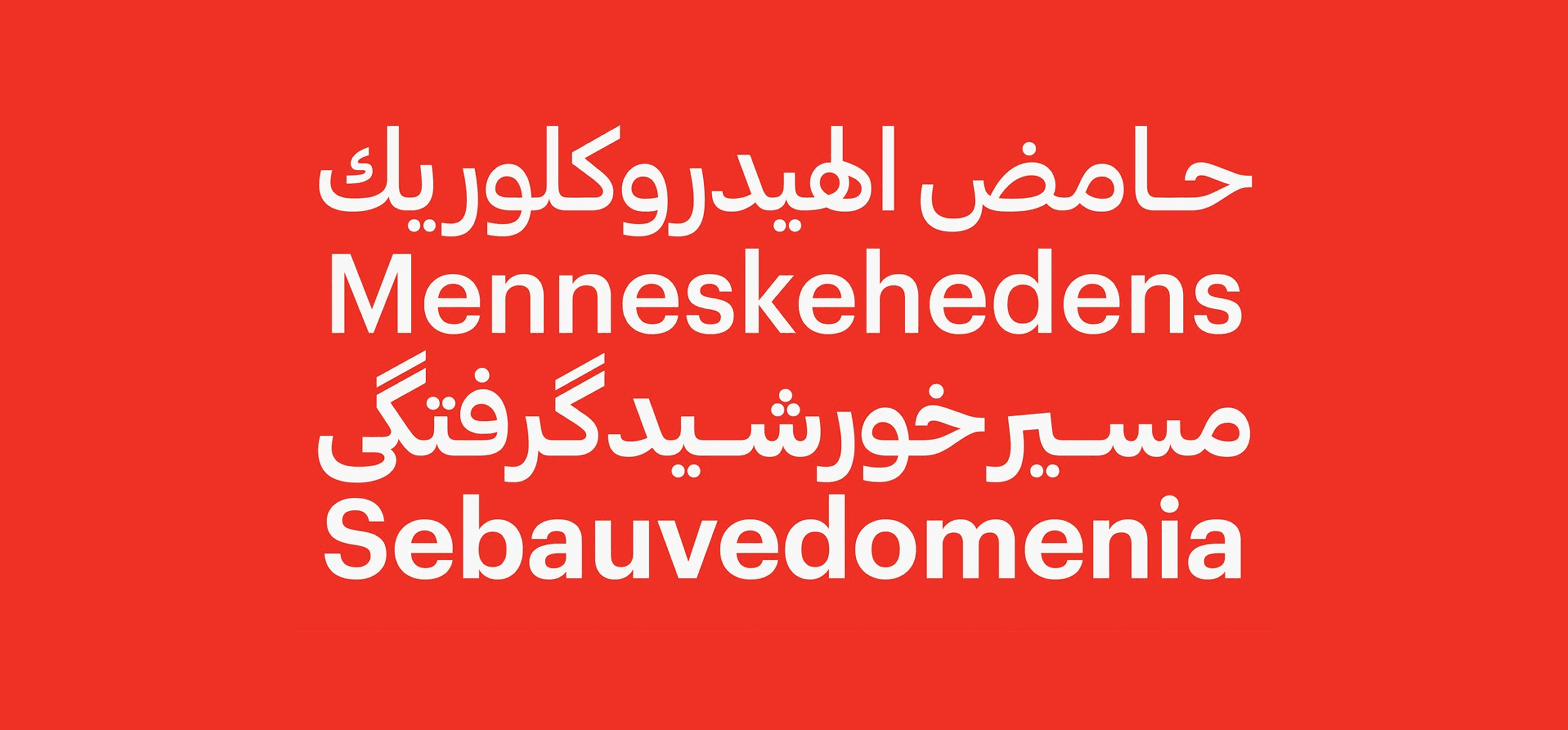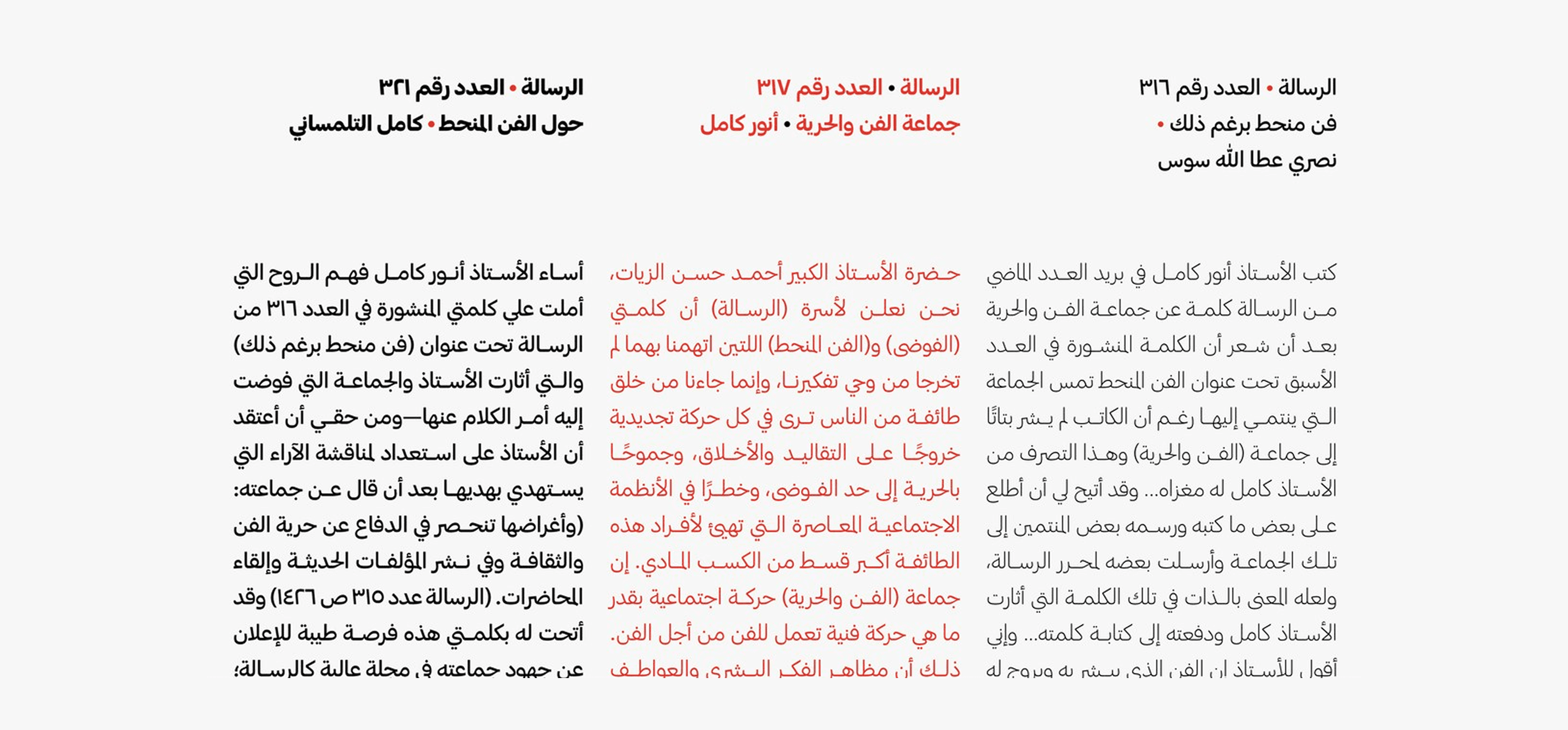
تم تصميم Graphik بواسطة كريستيان شوارتز (Christian Schwartz)، وقد استُلهم من أساليب التصميم الجرافيكي التعبيرية التي استخدمت خطوطًا بسيطة جدًا.
يمثل Graphik إعادة تصور للخطوط المغمورة من منتصف القرن العشرين، دون التأثر بتاريخ الخطوط الأشهر مثل Helvetica أو Univers أو Futura.
يضم الخط تسعة أوزان لاتينية، من الرقيق جدًا (Thin) إلى الفائق السماكة (Super)، ما يجعله مناسبًا لمجالات متعددة بدءًا من العناوين البارزة وحتى النصوص الطويلة.
تم تصميم Graphik بواسطة كريستيان شوارتز (Christian Schwartz)، وقد استُلهم من أساليب التصميم الجرافيكي التعبيرية التي استخدمت خطوطًا بسيطة جدًا.
يمثل Graphik إعادة تصور للخطوط المغمورة من منتصف القرن العشرين، دون التأثر بتاريخ الخطوط الأشهر مثل Helvetica أو Univers أو Futura.
يضم الخط تسعة أوزان لاتينية، من الرقيق جدًا (Thin) إلى الفائق السماكة (Super)، ما يجعله مناسبًا لمجالات متعددة بدءًا من العناوين البارزة وحتى النصوص الطويلة.
تم تصميم Graphik بواسطة كريستيان شوارتز (Christian Schwartz)، وقد استُلهم من أساليب التصميم الجرافيكي التعبيرية التي استخدمت خطوطًا بسيطة جدًا.
يمثل Graphik إعادة تصور للخطوط المغمورة من منتصف القرن العشرين، دون التأثر بتاريخ الخطوط الأشهر مثل Helvetica أو Univers أو Futura.
يضم الخط تسعة أوزان لاتينية، من الرقيق جدًا (Thin) إلى الفائق السماكة (Super)، ما يجعله مناسبًا لمجالات متعددة بدءًا من العناوين البارزة وحتى النصوص الطويلة.